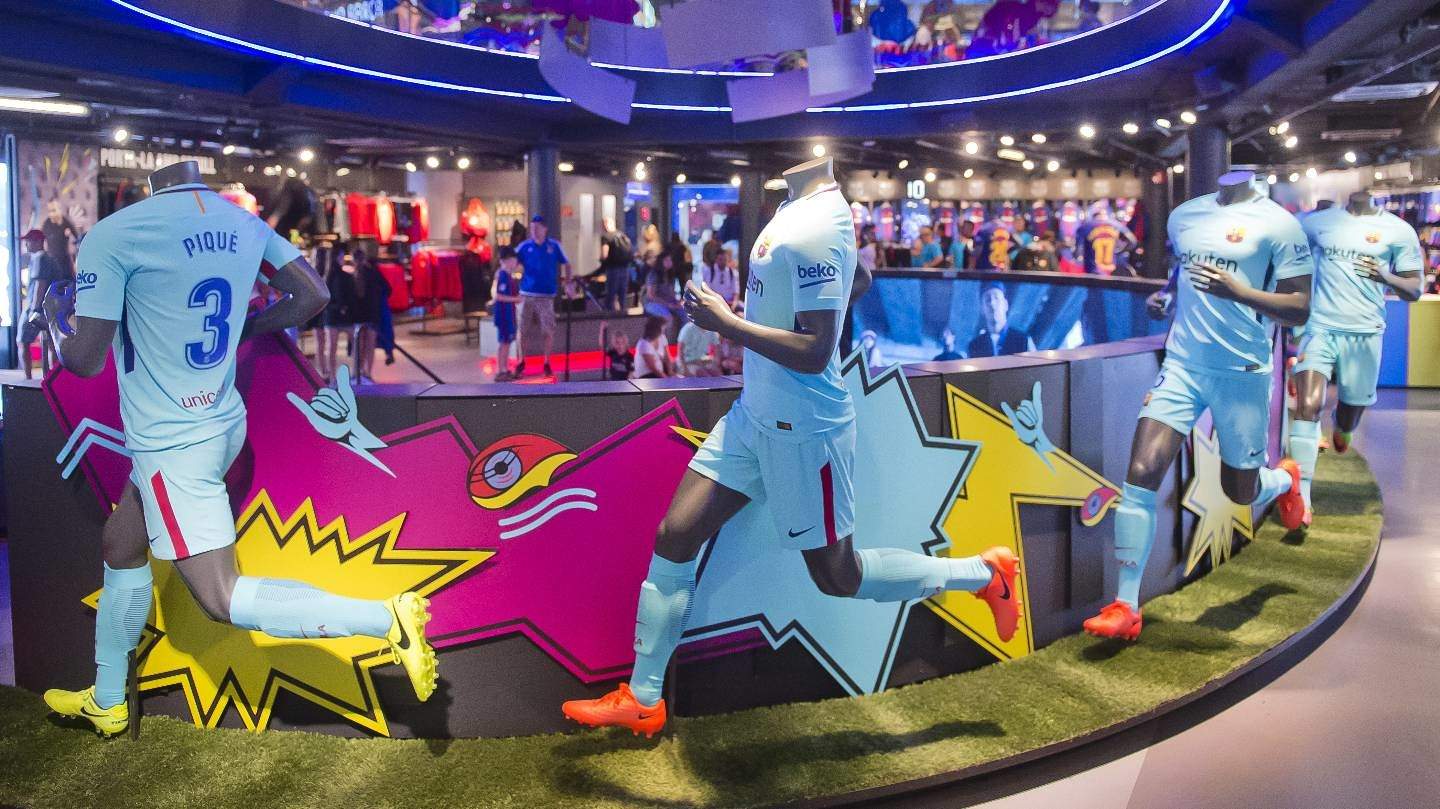
Barcelona 17-18 Auswärtstrikot-Schriftart enthüllt
Nachdem das Barcelona 17-18 Auswärtstrikot heute offiziell in den Verkauf geht, wurde uns ein Blick darauf gewährt, wie die neue Schriftart auf der Rückseite für Spielernamen und -nummern aussieht.
Mit Beginn in dieser Saison werden alle 20 Teams in der Liga die gleiche Schriftart für die Beschriftung auf der Rückseite verwenden und bis jetzt war die Reaktion, insbesondere bei Barcelonas Heimtrikot, wenig berauschend.
Barcelona 17-18 Auswärtstrikot-Schriftart
Dieses Bild zeigt die neue Schriftart auf der Rückseite des Barcelona 2017-2018 Trikots.
Es ist beim Auswärtstrikot besser. Weil die Zweitfarbe die gleiche Farbe wie das Trikot hat, was einen schönen Ausschnittseffekt erschafft, hat die Schriftart eine lässigere und dünnere Erscheinung. Nichtsdestotrotz ist die Kurve bei den Spielernamen weiterhin eher überflüssig.
Interessanterweise wird die Schriftart im gleichen Blauton wie das Nike-Logo auf der Vorderseite gehalten, obwohl das Unicef-Sponsorenlogo auf der unteren Rückseite rot gehalten ist. Bindet es gewissermaßen in den Rest des Trikots ein.